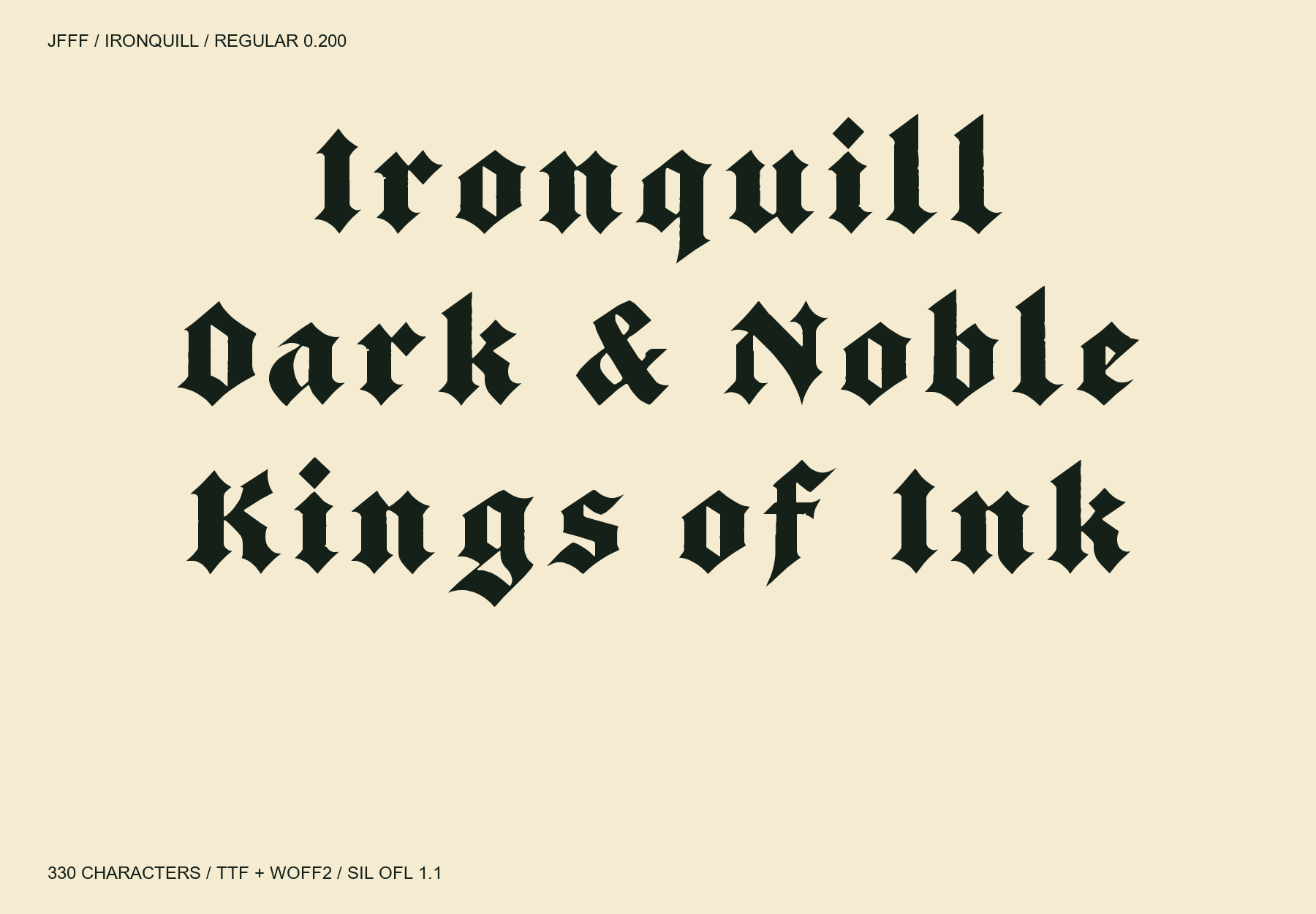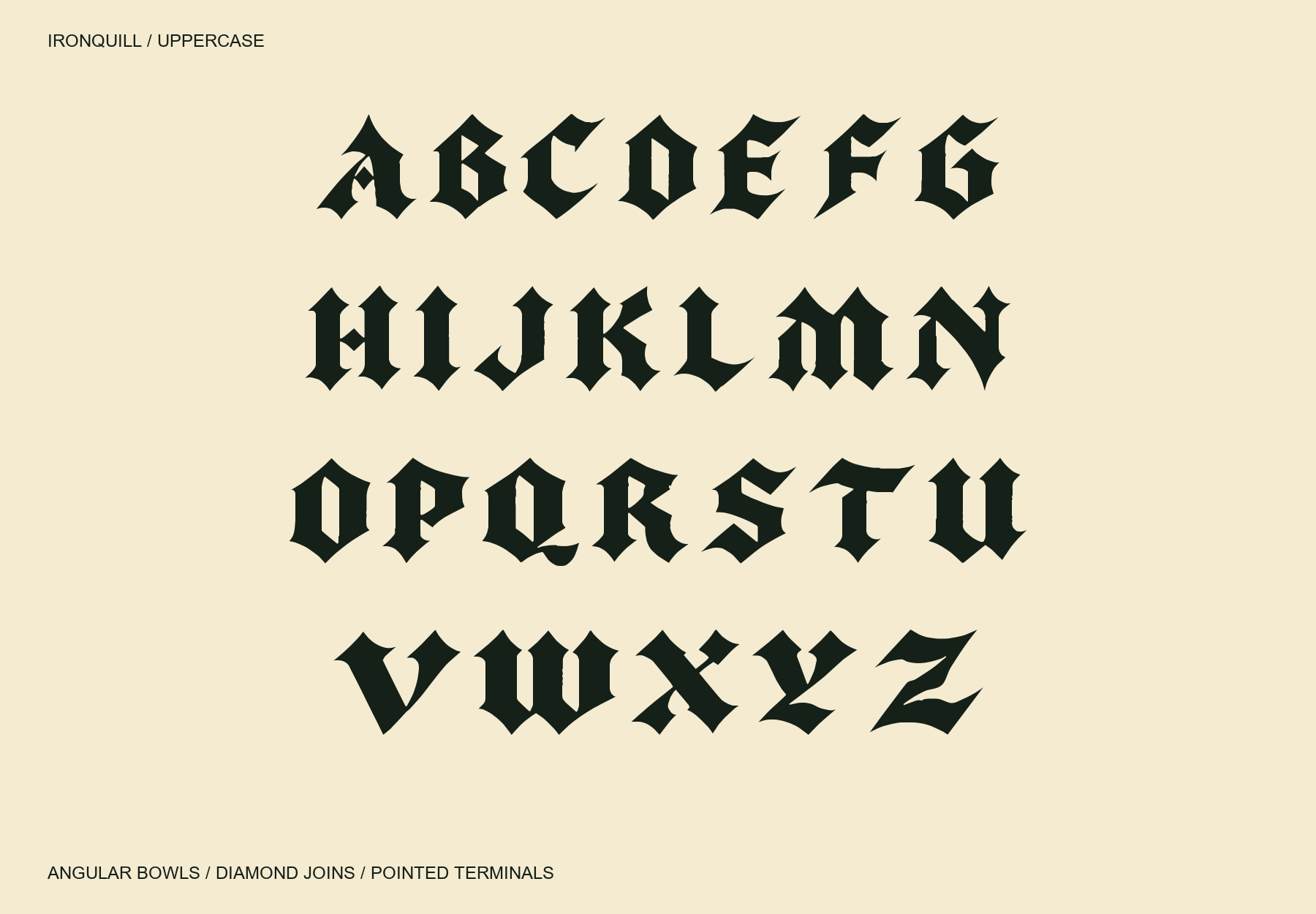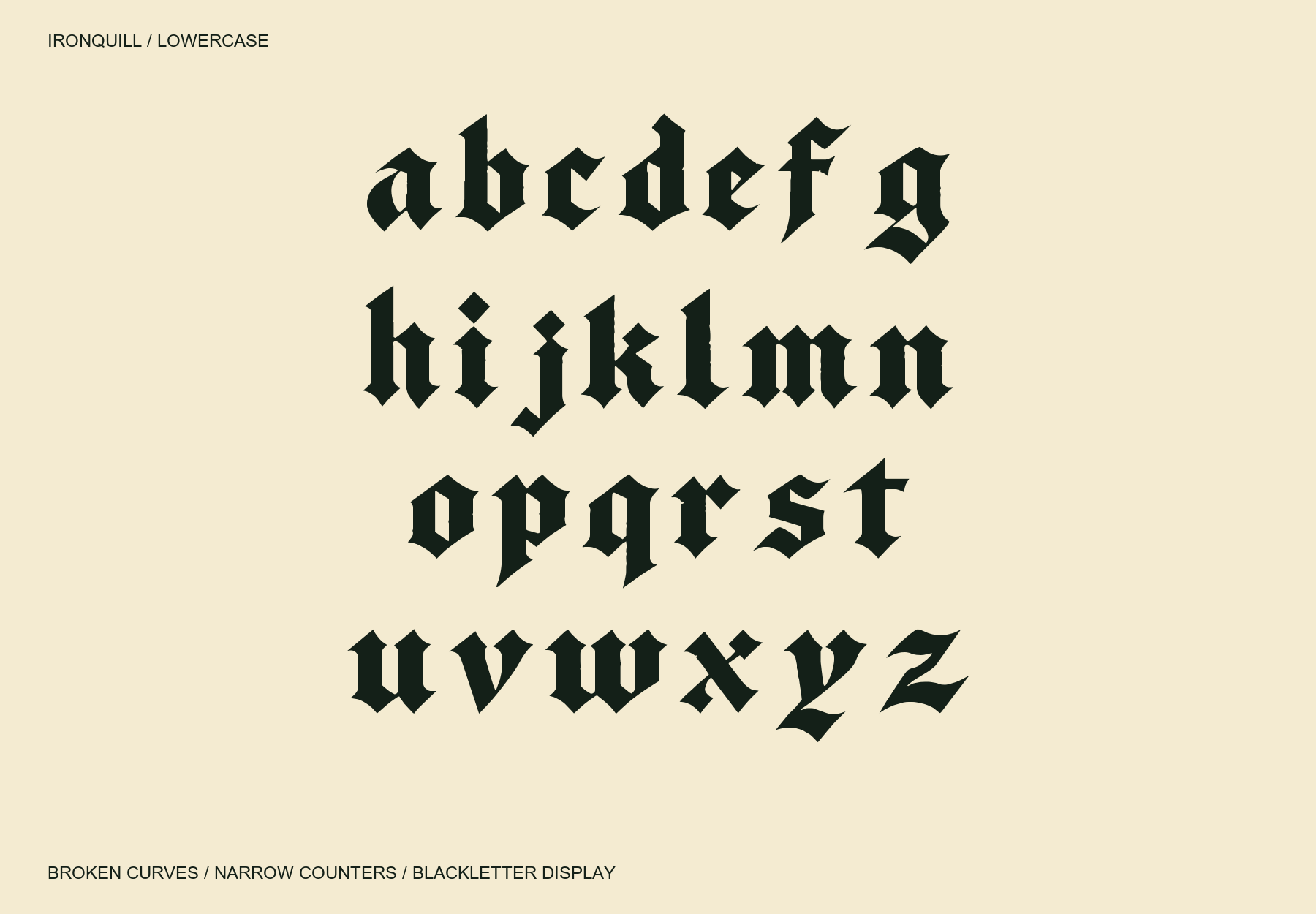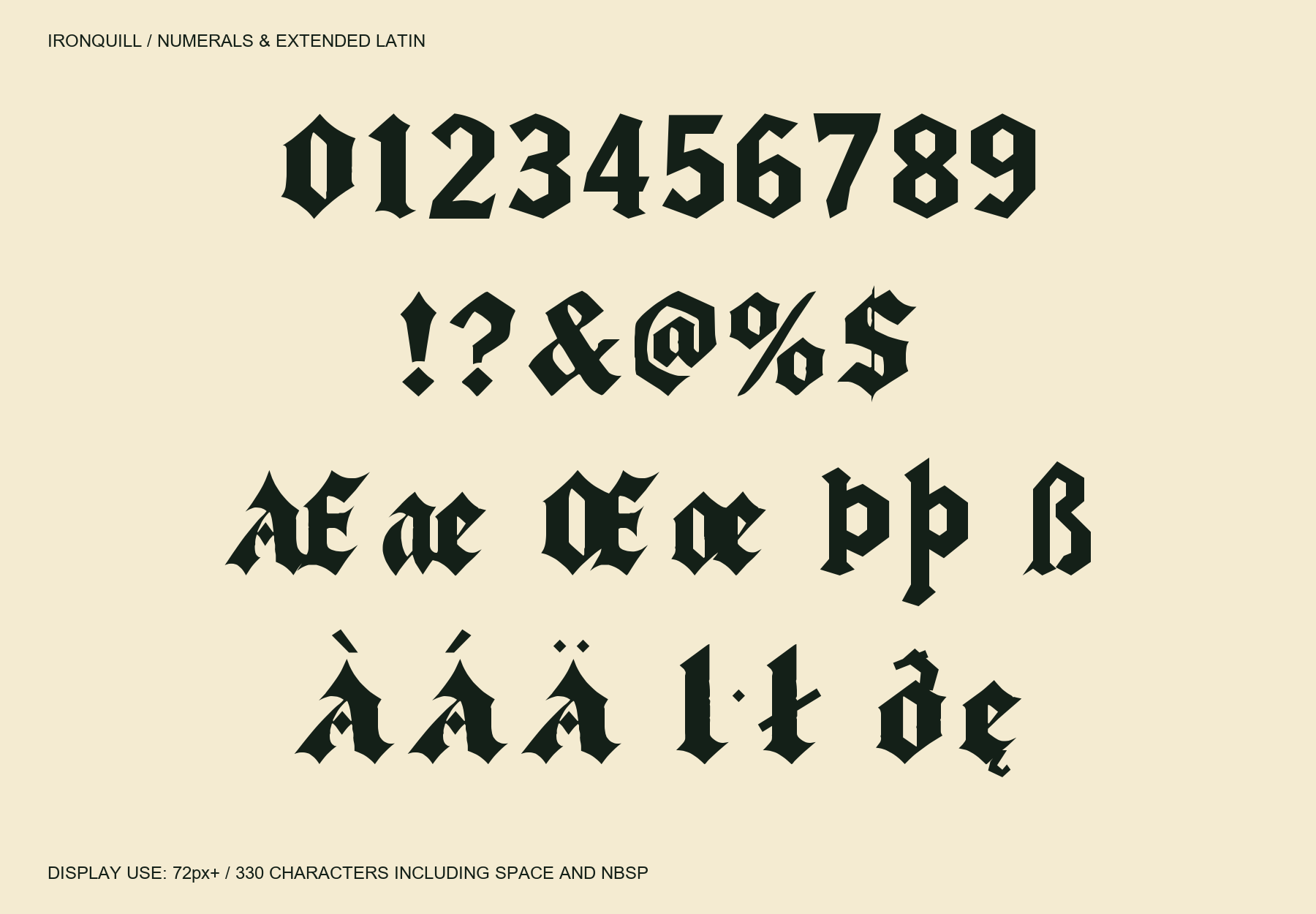
Ironquill은 굵은 수직 획, 각진 곡선과 좁은 속공간, 마름모 형태의 연결부와 점, 날카로운 획 끝이 특징인 블랙레터 디스플레이 서체입니다. 오목하게 휘어지는 끝부분과 단단한 골격으로 고전적인 인상을 표현합니다. Regular 0.200 · 라틴 330자(공백·NBSP 2자 포함). 영문 대소문자, 숫자, 확장 라틴 악센트와 기호를 지원하며 한글은 포함하지 않습니다. TTF와 WOFF2를 하나의 ZIP으로 제공하며 SIL Open Font License 1.1로 무료 배포합니다. 72px 이상 제목·포스터에 권장합니다. 작은 본문에서는 좁은 속공간과 장식적인 형태의 가독성이 낮아질 수 있습니다. 악센트 문자는 완성형 문자로 지원합니다. 330자 확대 검수와 형태 수정을 거쳤으며, 악센트 파생 조합을 포함한 937쌍의 커닝을 적용했습니다. 기본 68쌍과 악센트 예시 12쌍을 시각적으로 비교했습니다. 108,900개 인접 조합의 경계 검사에서 겹침이 발견되지 않았으며, 모든 조합을 수작업으로 커닝했다는 의미는 아닙니다. Windows 출력 및 Edge·Chrome 웹폰트 로딩·커닝을 확인했습니다. macOS와 Adobe·Office 앱 UI는 미검수입니다.